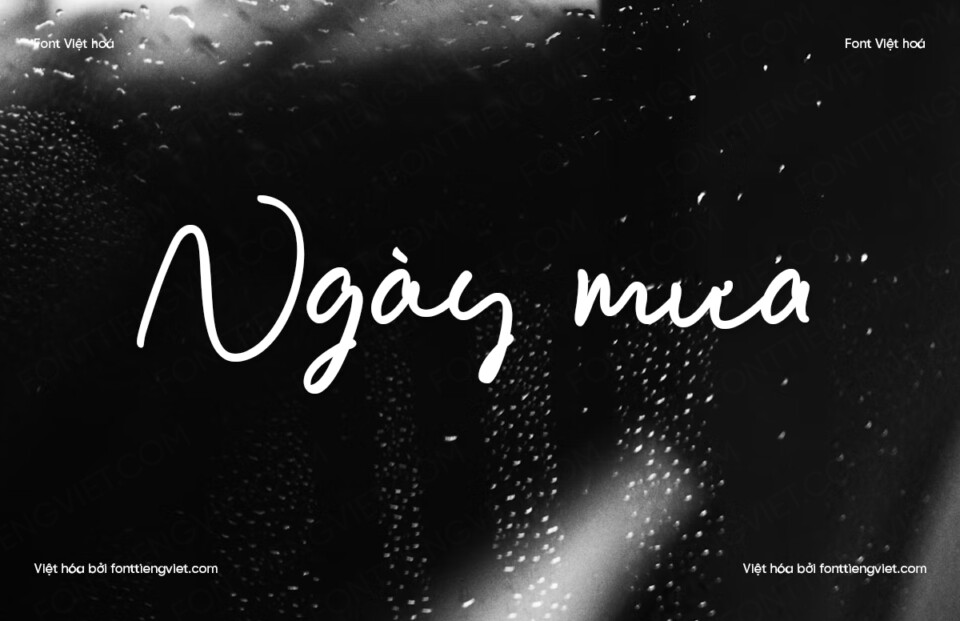
Tải Font Việt Hóa 1FTV VIP Butterfly Serenade – Nét Chữ Bay Bổng, Thanh Lịch Cho Thiết Kế
Bạn đang tìm kiếm một phông chữ mang đậm nét lãng mạn và sang trọng? Khám phá ngay font Việt hóa 1FTV VIP Butterfly Serenade – một tuyệt tác typography hoàn hảo giúp bạn nâng tầm mọi dự án thiết kế. Từ thiệp cưới, bao bì mỹ phẩm đến nhận diện thương hiệu, bộ font này chắc chắn sẽ làm hài lòng những designer khó tính nhất.
1. Phong Cách Thiết Kế Của Butterfly Serenade
Đúng như tên gọi, Butterfly Serenade mang đến một “giai điệu” hình ảnh nhẹ nhàng, bay bổng tựa như những cánh bướm. Đây là một bộ font nghệ thuật mang âm hưởng lãng mạn, nổi bật với những đường nét uốn lượn tinh tế, độ tương phản thanh – đậm rõ ràng và hài hòa. Sự kết hợp giữa vẻ đẹp cổ điển và hơi thở hiện đại giúp font chữ này dễ dàng thu hút ánh nhìn và tạo ra chiều sâu cảm xúc cho tác phẩm.
2. Ưu Điểm Nổi Bật Của Bản Việt Hóa 1FTV VIP
• Ký tự mở rộng phong phú: Hỗ trợ đầy đủ các ký tự thay thế (Alternate Glyphs) và các đường nét uốn lượn (Swashes) ở đầu/cuối chữ, cho phép bạn tự do sáng tạo những tiêu đề mang đậm tính cá nhân.
3. Tính Ứng Dụng Trong Đồ Họa
Với sự mềm mại và sang trọng, 1FTV VIP Butterfly Serenade là lựa chọn “chân ái” cho các ấn phẩm đòi hỏi tính thẩm mỹ cao: